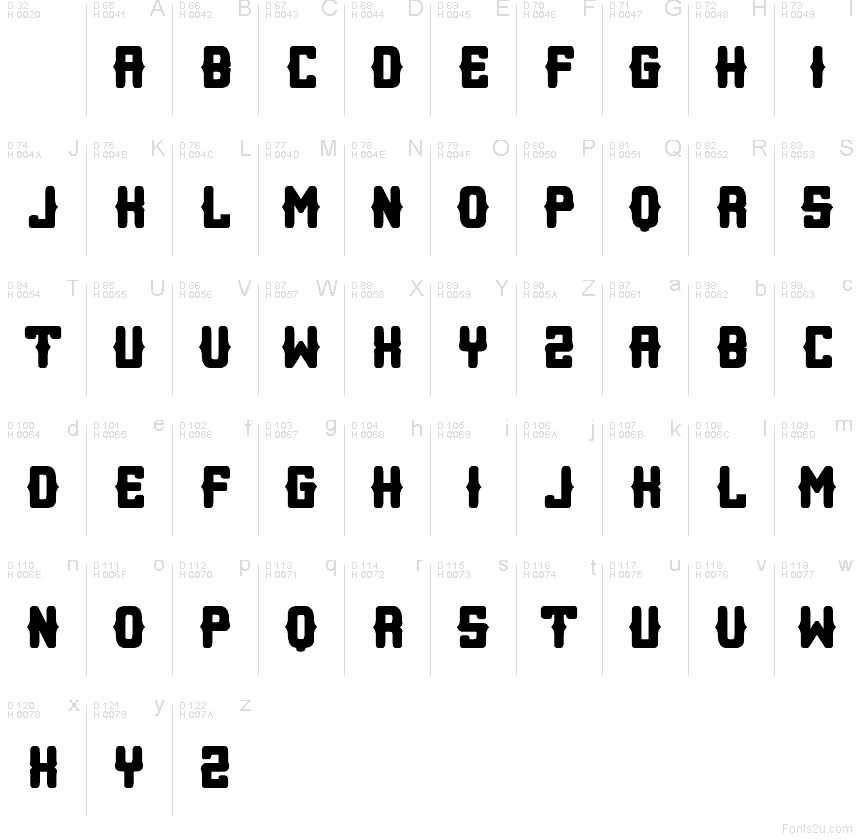
Sombrero Condensed od Vladimira Nikolica je bezplatné mexické písmo typu display. Tvoří ho mohutná bloková silueta s výrazným vtlačením směrem dovnitř, díky čemuž každé písmeno působí spíše vytesaným než kresleným dojmem. Opakující se efekt přesýpacích hodin v kombinaci se zaoblenými rohy a tupými horními hranami dodává nápisům charakter starých vývěsních štítů v cantinách a sváteční grafiky.
Sombrero Condensed je jako stvořené pro nabídky v taco stáncích, etikety na tequilu, letáky na Cinco de Mayo, branding restaurací či plakáty na akce. Písmo má dostatečnou vizuální sílu na to, aby uneslo hlavní nadpisy bez potřeby dalších ozdob. Zúžené středy vytvářejí stabilní rytmus, který vynikne na obalech, výlohách i tematických příspěvcích na sociálních sítích, kde záleží na silném kulturním odkazu.